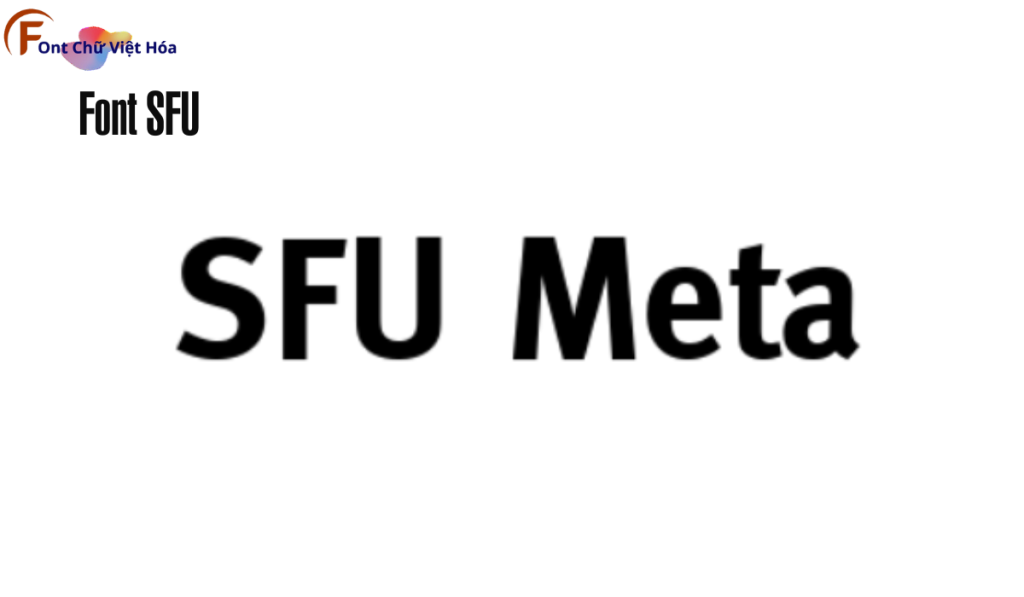
Font SFU Meta Việt Hóa
Bộ Font: SFU
Phân loại: Hiện đại, Thanh lịch
Kiểu chữ: Sans-serif
Độ dày: Regular, Bold, Italic, Bold Italic
Font SFU Meta Việt Hóa, thuộc bộ font SFU, mang phong cách sans-serif hiện đại với các đường nét thanh thoát và tinh tế. Font này được thiết kế nhằm mục tiêu tạo ra sự rõ ràng và dễ đọc, đặc biệt phù hợp cho các thiết kế như poster, logo, và tiêu đề. Đặc điểm hình dạng của SFU Meta là các đường nét sắc sảo và tỷ lệ chữ cân đối, giúp tối ưu hóa không gian trong thiết kế và tạo ấn tượng thị giác mạnh mẽ. Font này cũng đã được Việt hóa, mang đến sự linh hoạt và tiện dụng cho các dự án thiết kế bằng tiếng Việt, giúp người dùng dễ dàng tiếp cận và sử dụng.